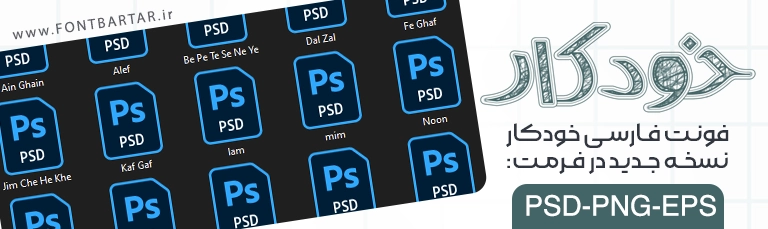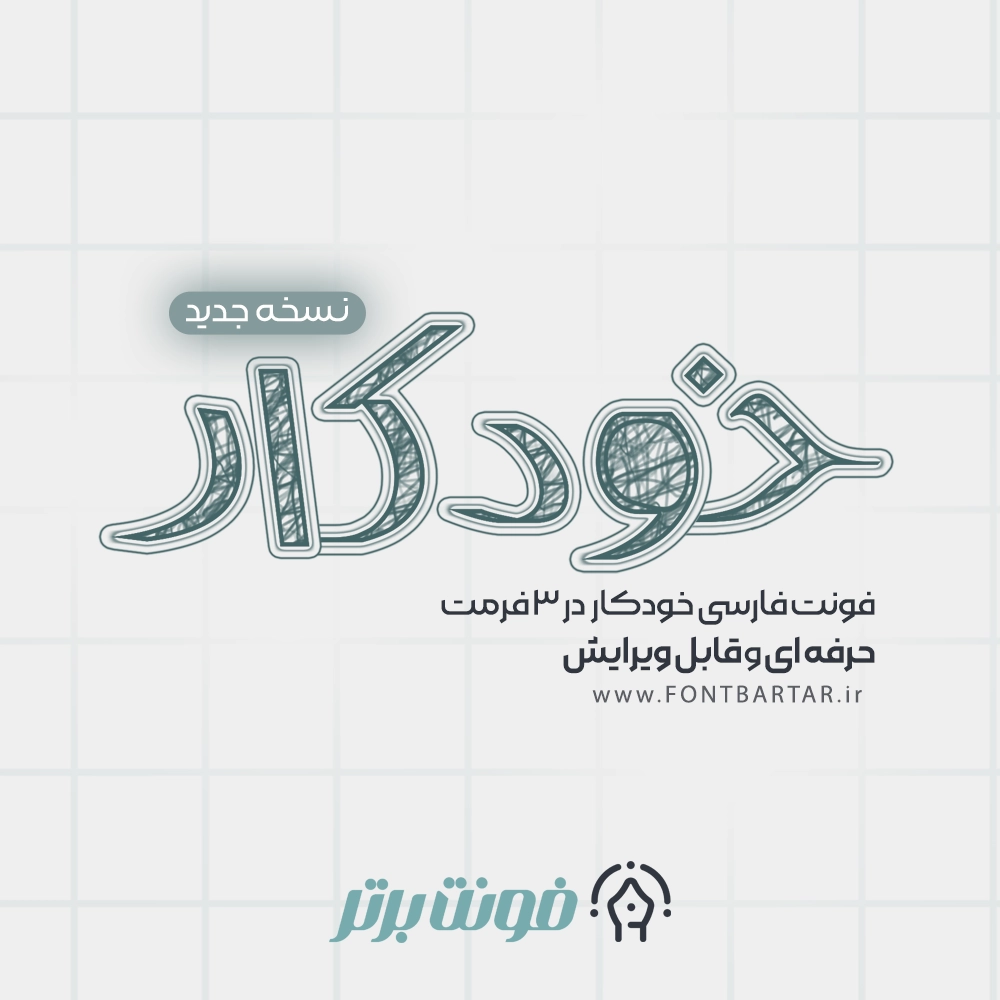
فونت لایه باز خودکار
فونت فارسی خودکار
Khodkar Font
فونت فارسی خودکار
دانلود فونت لایه باز خودکار – فونت نوستالژی و دست‌نویس حرفه‌ای
فونت فارسی خودکار یکی از محبوب‌ترین فونت‌های دست‌نویس است که حال‌وهوای نوستالژی دوران مدرسه، دفتر مشق و یادداشت‌های روزمره را تداعی می‌کند. خرید فونت فارسی با طراحی خلاقانه و طبیعی، حس دست‌خط واقعی با خودکار را به متن‌ها اضافه می‌کند و باعث می‌شود نوشته‌های شما صمیمی‌تر و جذاب‌تر دیده شوند.
اگر به دنبال فونتی هستید که هم خاص و متفاوت باشد و هم بتواند ارتباط انسانی عمیقی با مخاطب برقرار کند، فونت خودکار بهترین انتخاب شماست.
فونت خودکار بر خلاف سایر فونت ها به صورت لایه باز بوده (psd) و امکان تایپ مستقیم در نرم افزار ها را ندارد همچنین شامل تمامی حروف از الف تا ی می شود این فونت به چینش های مختلف می تواند در کمترین زمان این امکان را به طراح بدهد که یک لوگو تایپ حرفه ای برای کسب و کار های مختلف طراحی کند ویژگی های این فونت حرفه ای را باهم مرور کنیم.
ویژگی‌های فونت خودکار
• طراحی کاملاً شبیه دست‌خط طبیعی با خودکار
• مناسب برای پوستر، لوگو، جلد کتاب، کارت تبریک و شبکه‌های اجتماعی
• حس صمیمیت، سادگی و نوستالژی در متن‌ها
چرا باید فونت جدید خودکار را انتخاب کنیم؟
فونت لایه باز خودکار فقط یک فونت ساده نیست؛ بلکه یک تجربه احساسی و هنری است. این فونت باعث می‌شود نوشته‌های شما مانند یک دست‌خط واقعی به نظر برسند و به راحتی با ذهن و احساس مخاطب ارتباط برقرار کنند.
استفاده از فونت خودکار در طراحی باعث افزایش جذابیت بصری، ماندگاری در ذهن کاربر و ایجاد یک حس دوستانه می‌شود که برای تبلیغات و برندینگ بسیار مؤثر است.
کاربردهای فونت خودکار در طراحی
• طراحی پوسترهای خلاقانه و تبلیغاتی
• ساخت تایپوگرافی‌های حرفه‌ای
• طراحی جلد کتاب‌ها و دفترچه‌ها
• استفاده در استوری و پست‌های اینستاگرام
• طراحی کارت دعوت، کارت تبریک و نوشته‌های شخصی
• ایده‌آل برای پروژه‌های هنری و گرافیکی با حال‌وهوای صمیمی